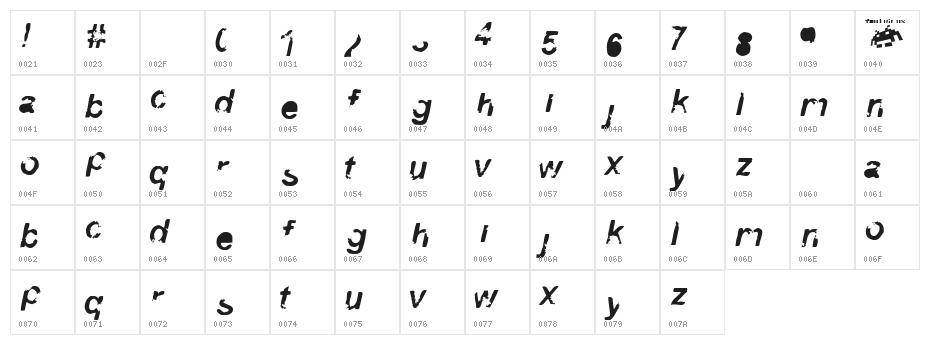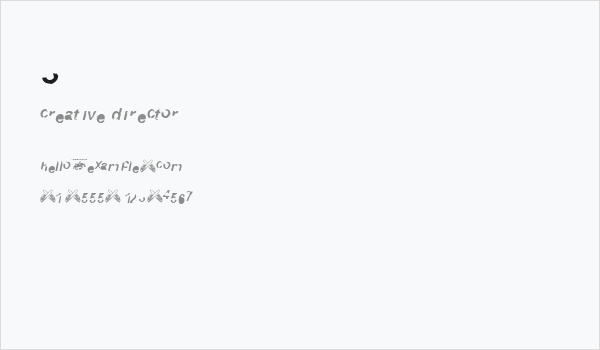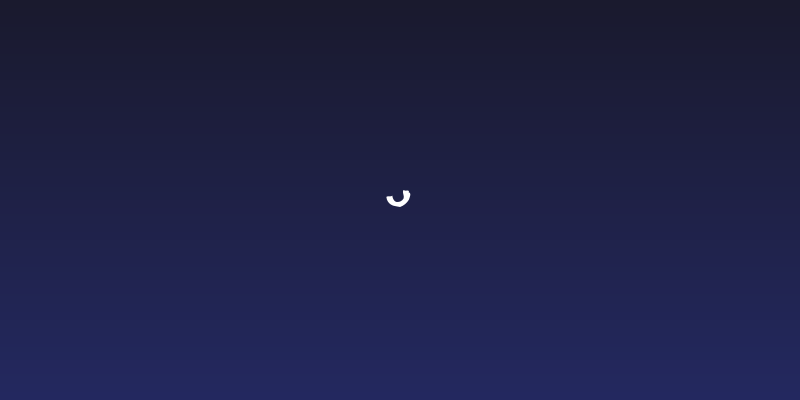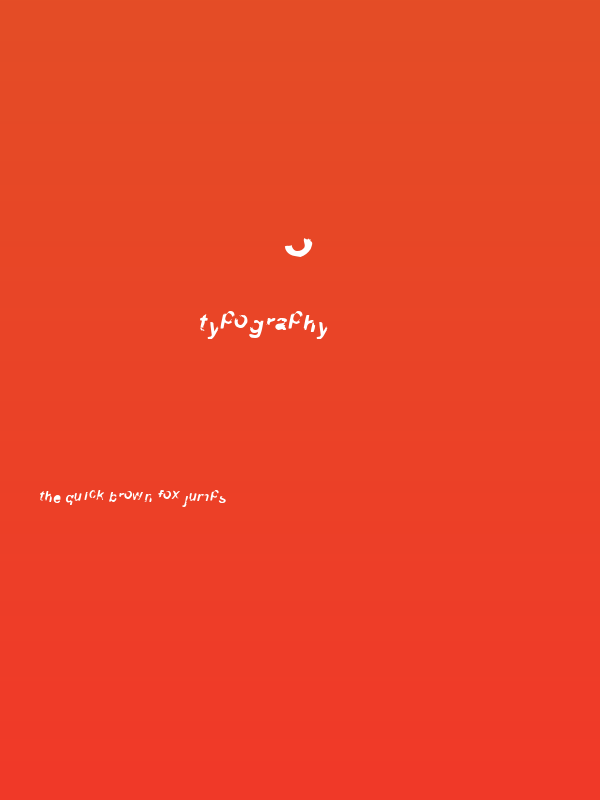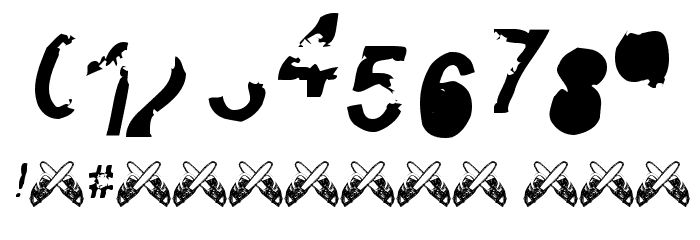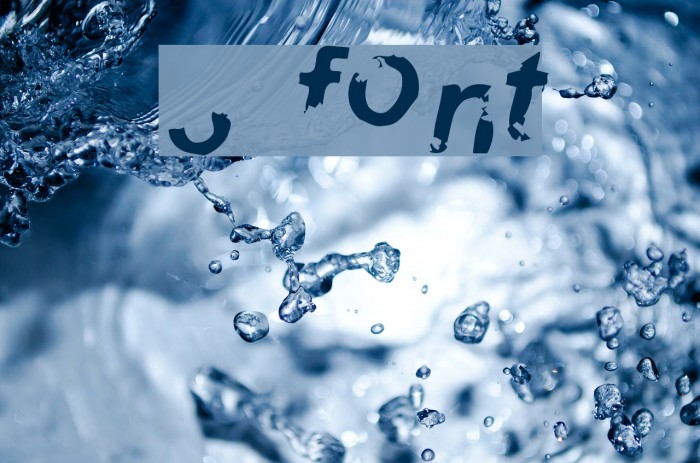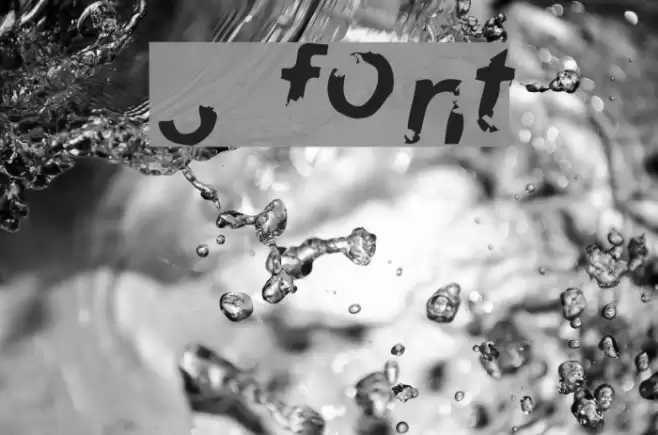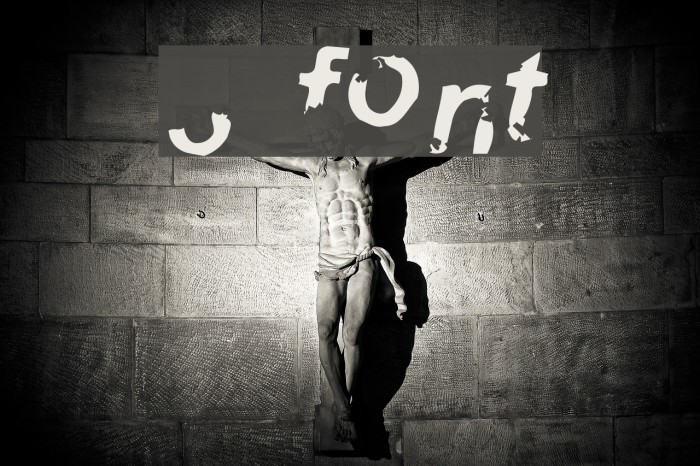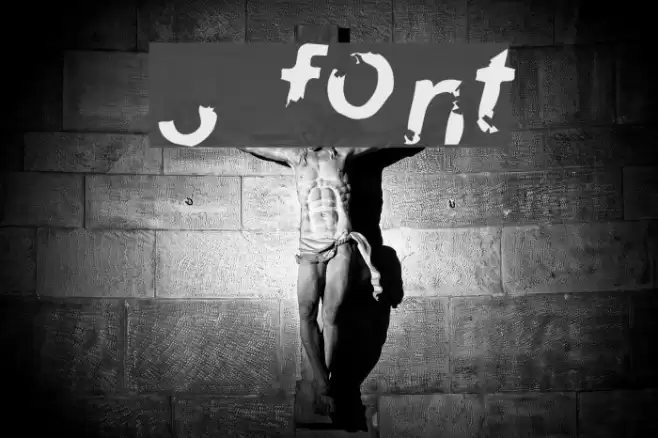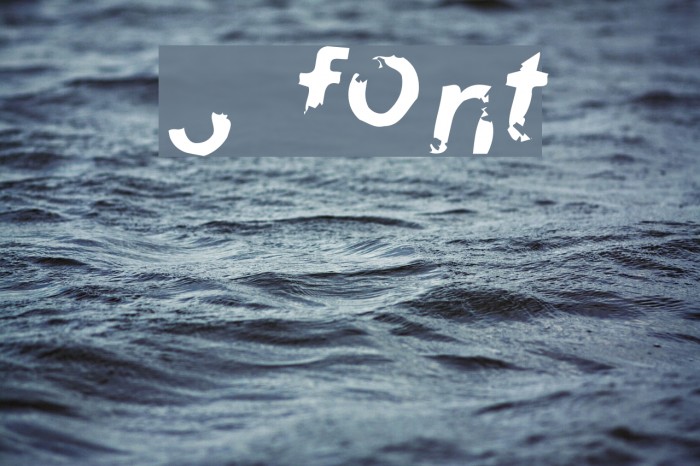
3 Font
✎ Distorted Eroded
| Kategorien | Distorted Eroded |
| Gesamtstil | Grunge, Distressed |
| Vorgeschlagene Projekte | Album covers, graffiti art, urban-themed posters, edgy branding materials. |